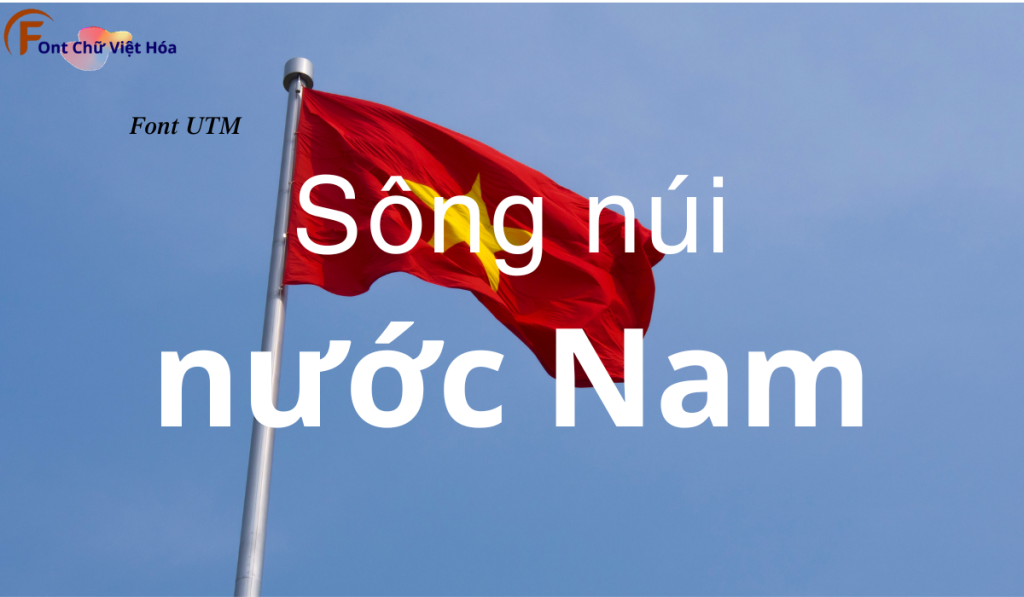
Font UTM Helve Việt Hóa
Tác giả: UTM Helve
Bộ Font: UTM
Phân loại: Hiện đại, Đơn giản
Kiểu chữ: Sans-serif
Độ dày: Regular, Bold, Italic, Bold Italic
Font UTM Helve Việt Hóa là một font chữ không chân đơn giản, thuộc bộ font UTM. Được thiết kế với mục tiêu mang lại sự hiện đại và dễ đọc, font này lý tưởng cho các dự án thiết kế như giao diện người dùng, ứng dụng di động, và website. Với các nét chữ rõ ràng và độ dày đều đặn, Font UTM Helve Việt Hóa không chỉ dễ đọc mà còn tạo cảm giác hiện đại và chuyên nghiệp. Việc Việt hóa font giúp người dùng dễ dàng tích hợp vào các thiết kế tiếng Việt, mang lại sự tiện lợi và nâng cao tính thẩm mỹ.